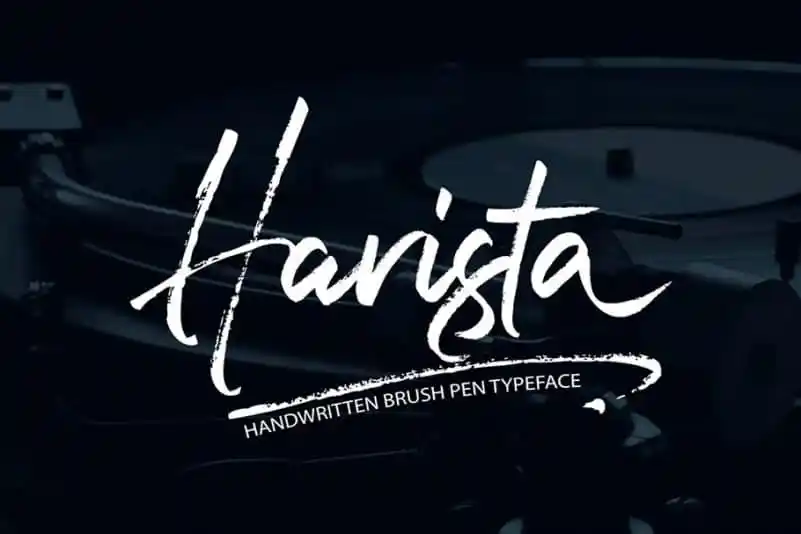
Harista Brush Font – Download Grátis
A Harista Brush Font é uma elegante tipografia de escrita filigranada criada por joelmaker usando caneta filigree. Este estilo sofisticado e fluido é perfeito para dar um ar suave a qualquer projeto gráfico, sendo especialmente adequado para aplicação em projetos de marca, embalagens de produtos, cartões de visita, logotipos e outros trabalhos visuais. Com seus traços fluidos e detalhes meticulosamente criados, a Harista Brush Font oferece uma maneira perfeita de adicionar elegância e sofisticação aos designs, tornando-o um recurso indispensável para designers gráficos em busca de fontes de estilo chamativo que se destacam na cena. Ideal tanto para projetos pessoais quanto profissionais, a Harista Brush Font é uma escolha inteligente para quem deseja manter uma identidade visual única e sofisticada em seus trabalhos visuais.